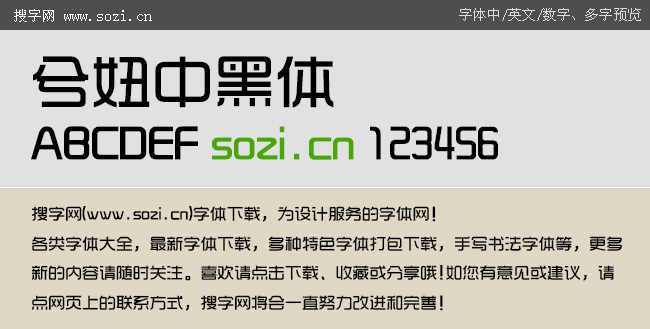
兮妞中黑體
搜字網(wǎng)提供一款兮妞中黑體中文字體下載,兮妞中黑體是一款筆畫(huà)圓潤(rùn)的中文藝術(shù)字體,字體端正,筆畫(huà)流暢,適合應(yīng)用于廣告設(shè)計(jì)、名片設(shè)計(jì)、包裝印刷、產(chǎn)品設(shè)計(jì)等應(yīng)用。